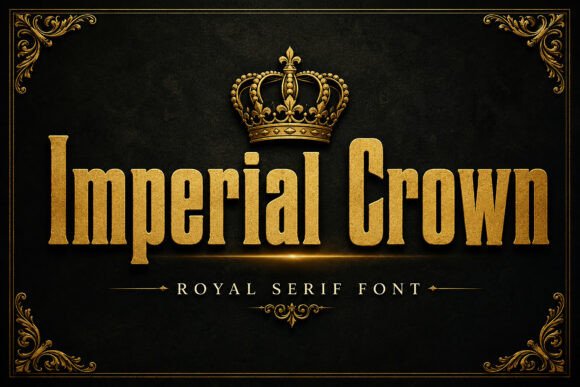
Imperial Crown
適切なデザイン要素を見つけるのは難しい場合がありますが、Imperial Crownは作品を即座に引き立てる優れたコレクションを提供します。
POD(オンデマンド印刷)製品、結婚式の招待状、またはソーシャルメディアのグラフィックを作成している場合でも、Imperial Crownは理想的です。